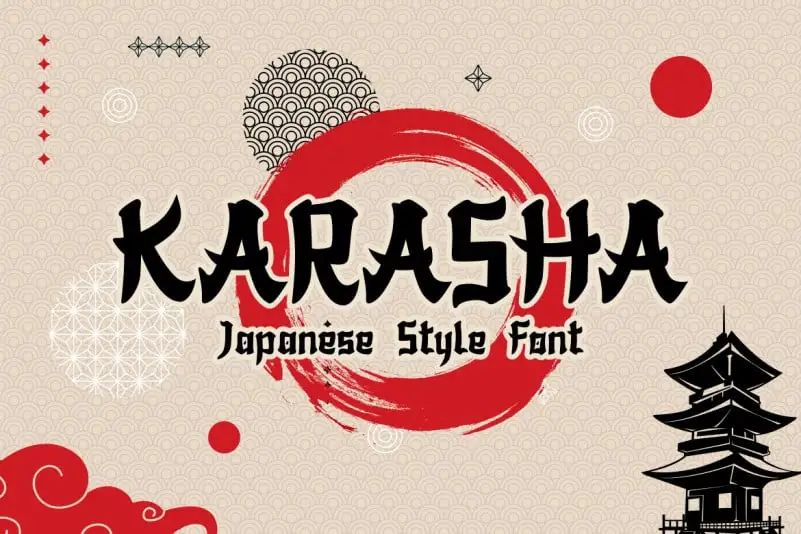
Karasha Display Font – Download Grátis
Karasha Display Font é uma fonte para exibição que traz a sofisticação japonesa diretamente às suas criações digitais. Com sua elegância e graça, esta fonte oferece um toque oriental inegável a qualquer texto aplicado. Perfeita tanto para cartazes quanto para design de websites ou editoriais que buscam um ar estilizado do Japão, Karasha Display é uma escolha ideal para quem quer incorporar elementos asiáticos em seus trabalhos, mas sem deixá-los aparentemente estranhos. Seja você designer gráfico, webmaster ou criador de conteúdo online, Karasha Display oferece um meio simples e elegante para adicionar uma dose específica de sofisticação ao seu design. Com sua rica presença visual e estilo único, esta fonte é como um passo à frente em tornar seus projetos ainda mais vibrantes e intrigantes.